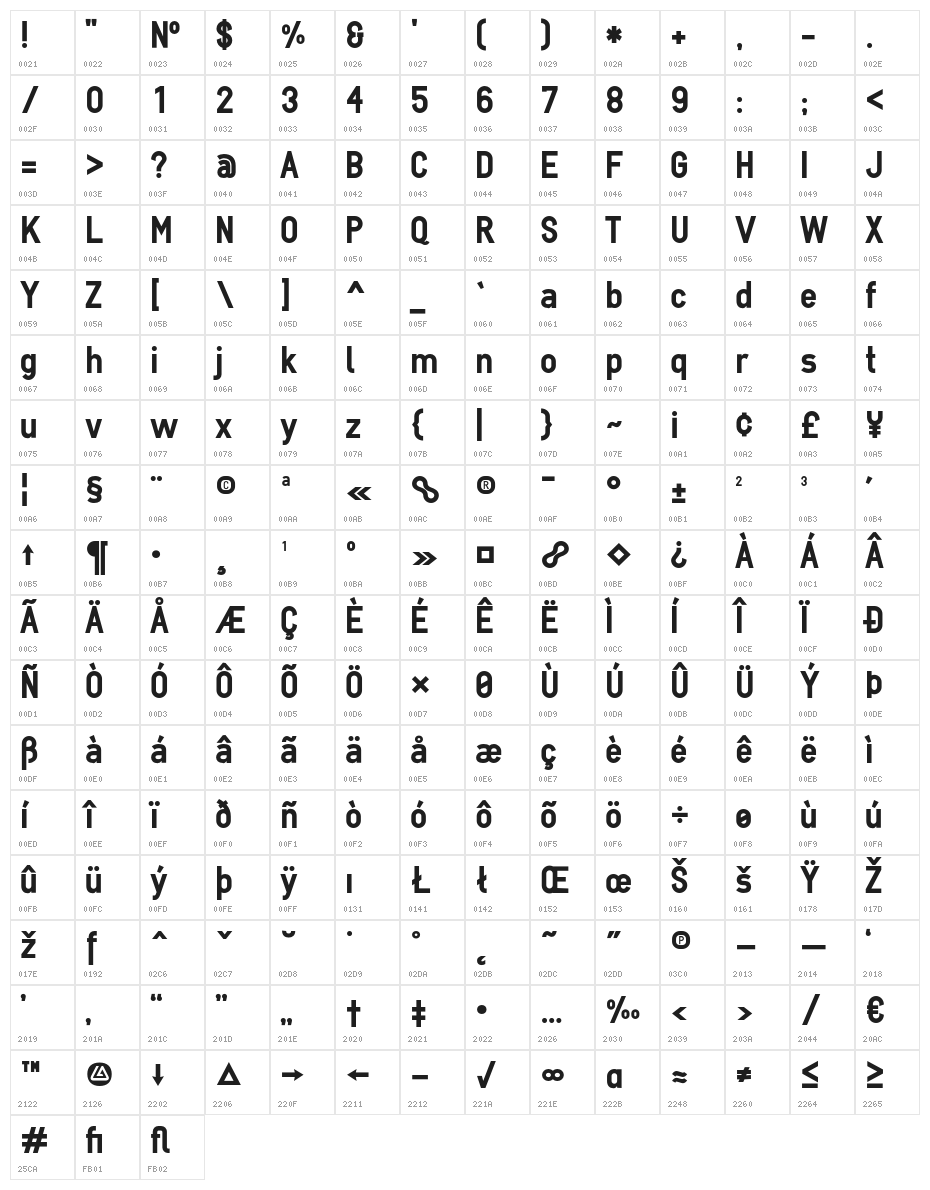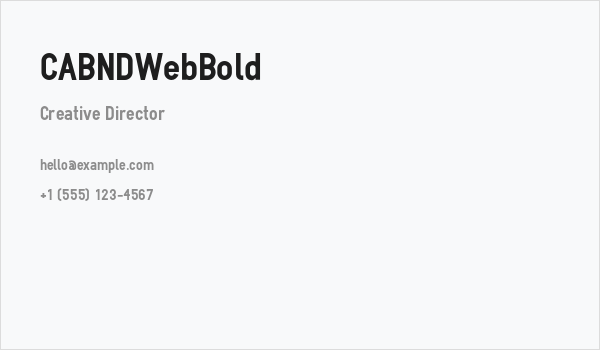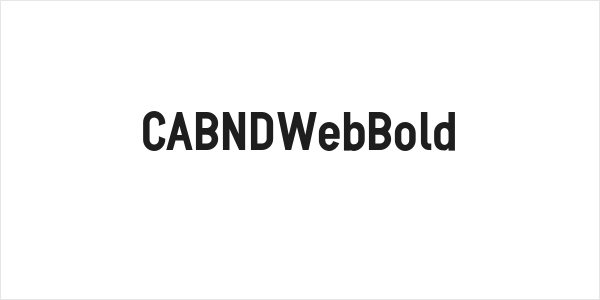
CABNDWebBold Font
✎ Sans Serif
| Proyectos propuestos | Ideal for branding, headlines, posters, and digital media where a strong, modern presence is needed. |